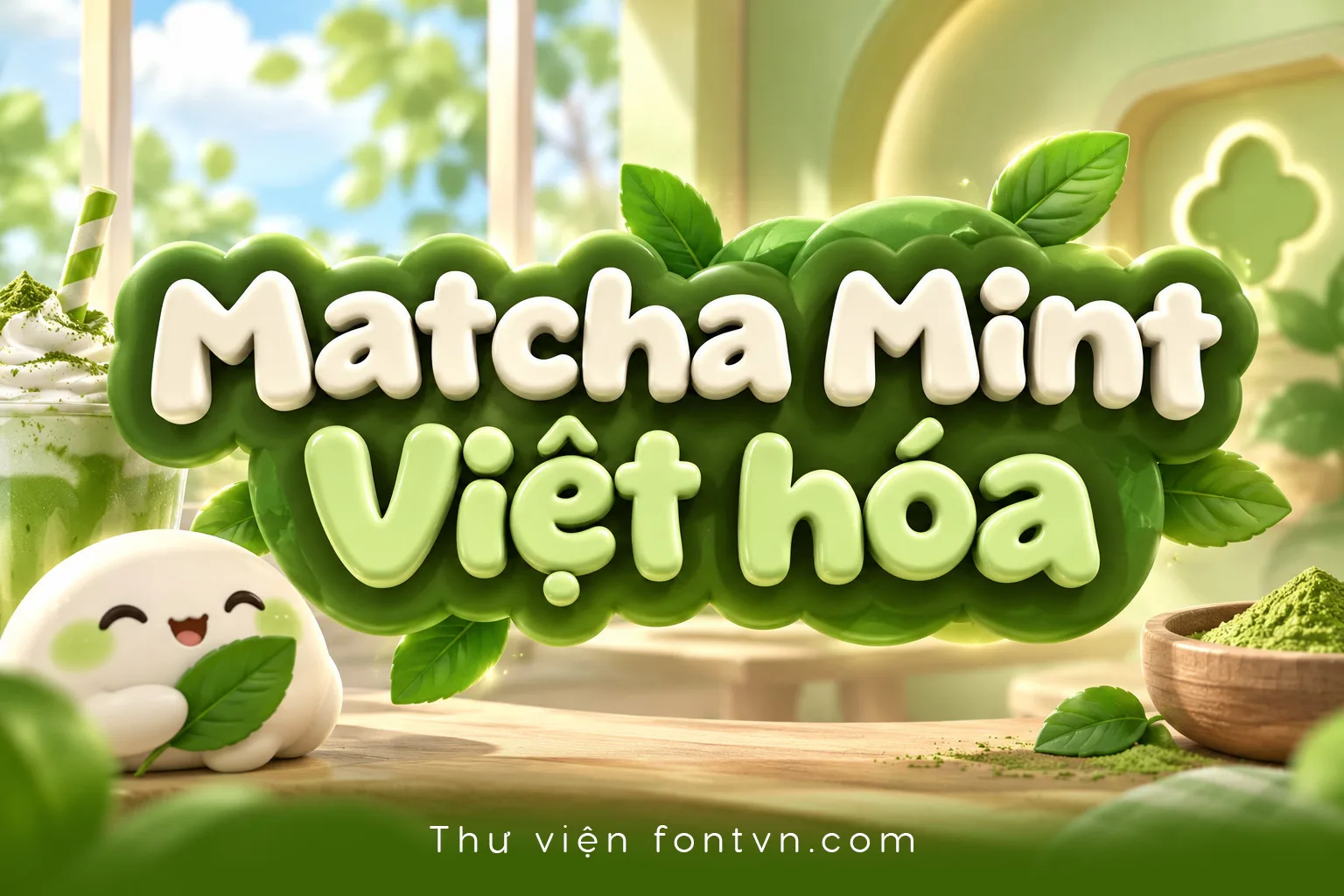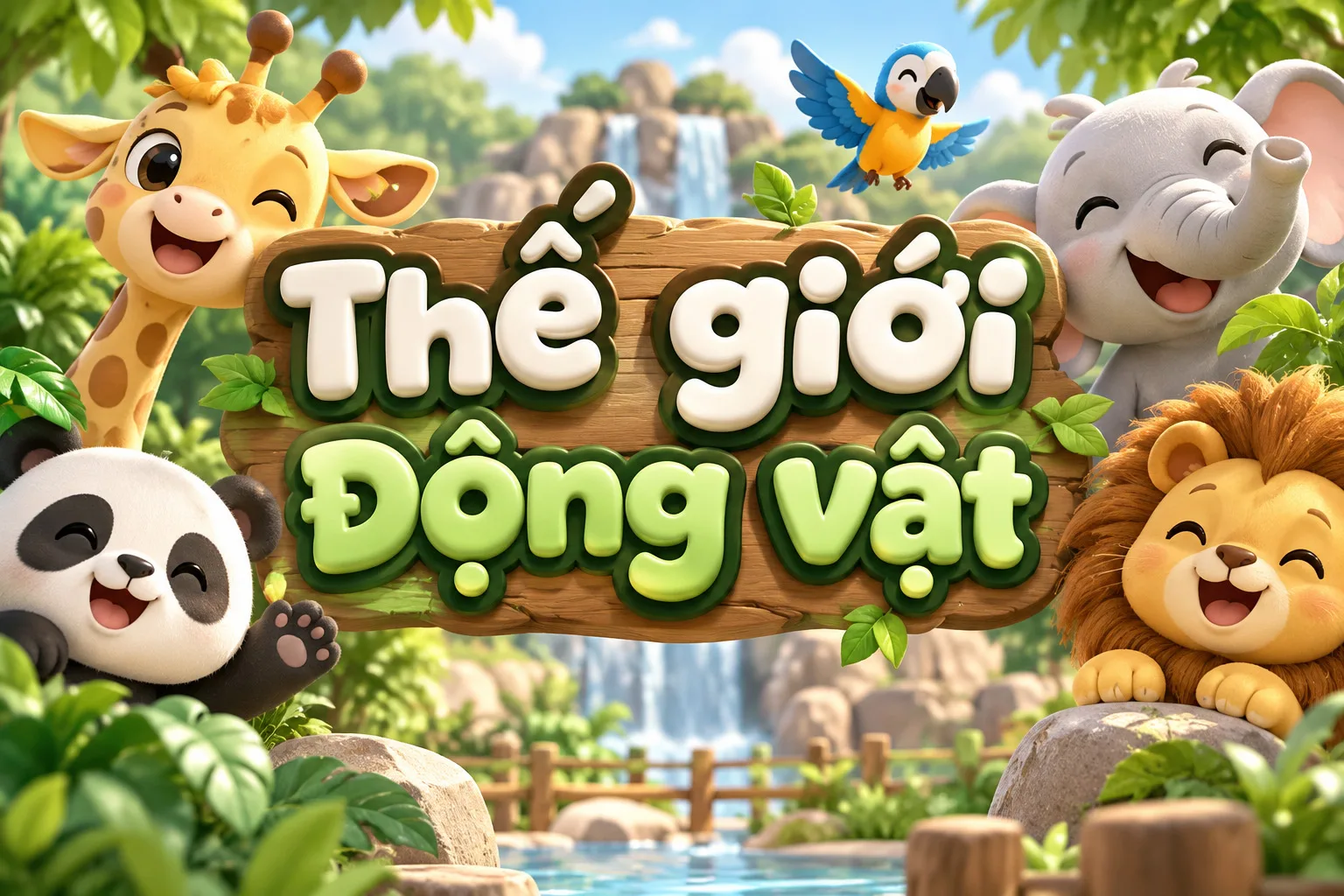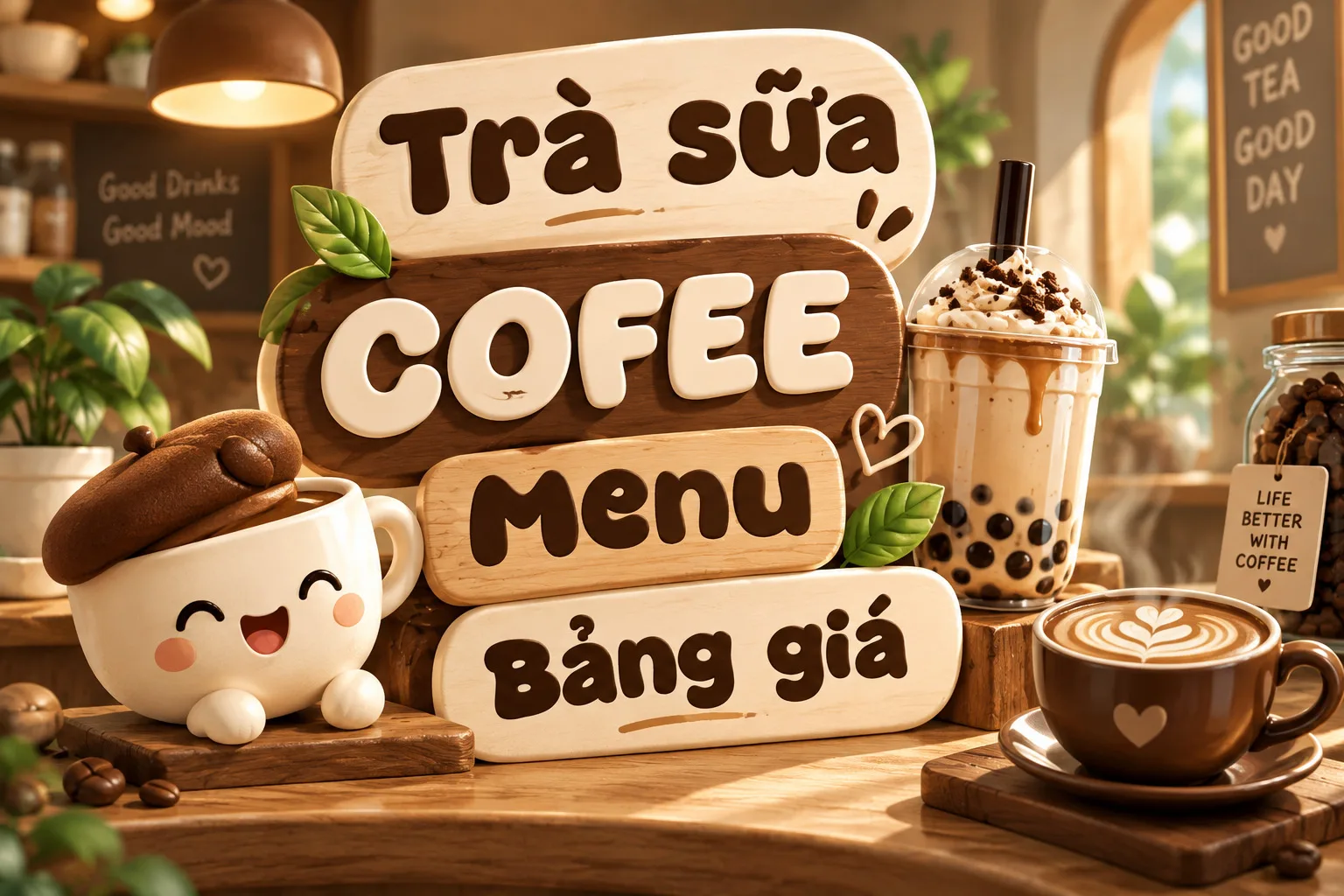
DVN – Matcha Mint Việt hóa – Font Chữ Bo Tròn Mềm Mại, Đáng Yêu & Đầy Cá Tính
Matcha Mint Việt Hóa là kiểu chữ display mềm mại, mũm mĩm và đầy tính vui nhộn. Font gây ấn tượng với các nét chữ bo tròn, dày, organic cùng những đường cong tự nhiên, tạo cảm giác thân thiện và trẻ trung ngay từ cái nhìn đầu tiên.
Thiết kế của Matcha Mint mang hơi hướng playful typography, phù hợp với các dự án cần sự đáng yêu, gần gũi nhưng vẫn nổi bật. Các ký tự có hình dáng hơi bất quy tắc giúp phần chữ trở nên sinh động hơn, đặc biệt khi sử dụng ở kích thước lớn.